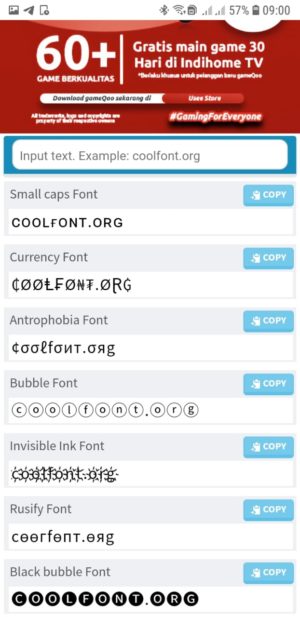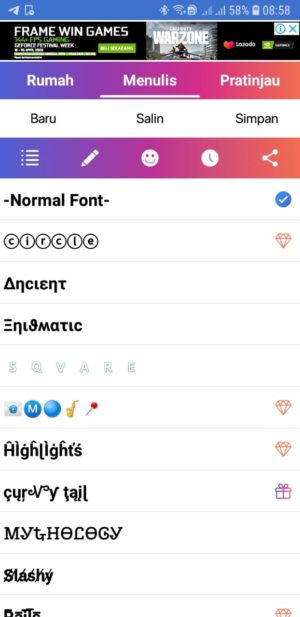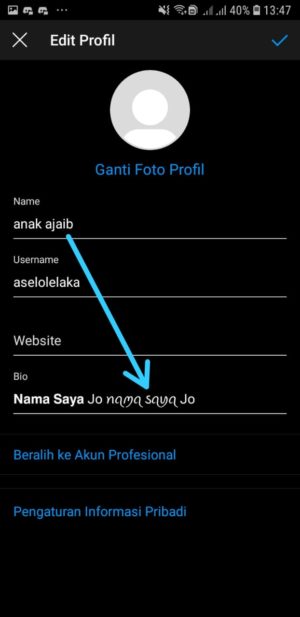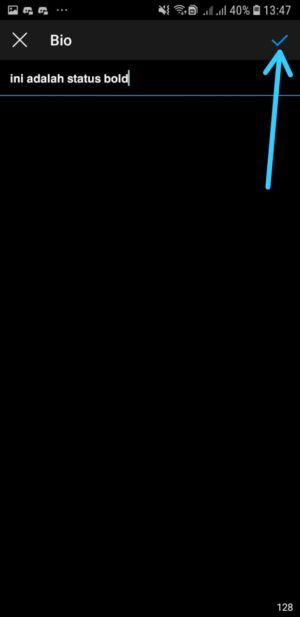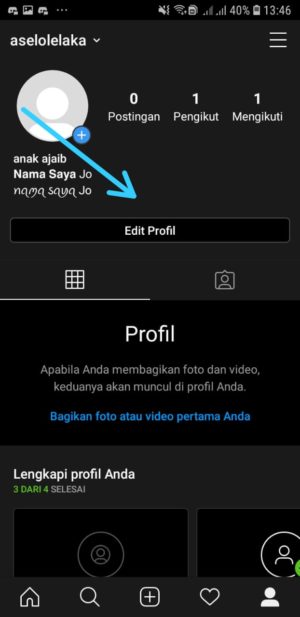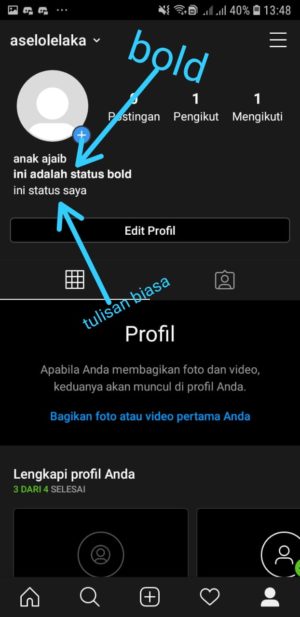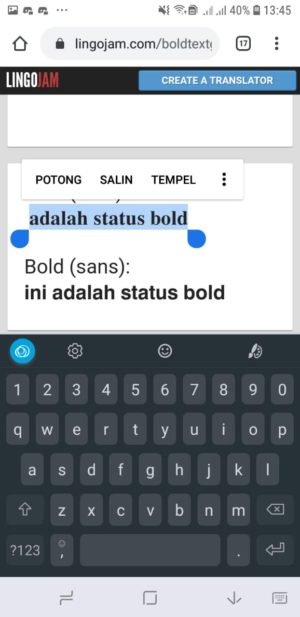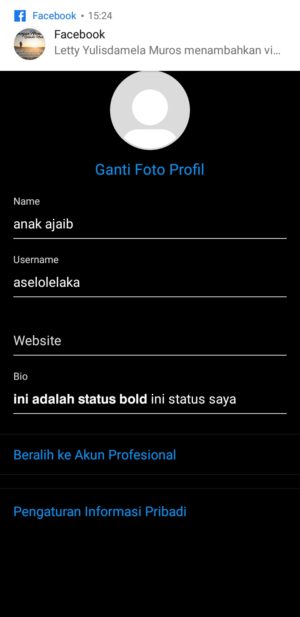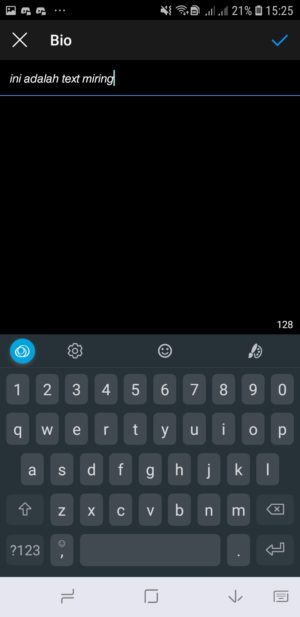
√ Cara Pakai Font Bold, Miring, Atau υɳιƙ Di Bio Instagram
Langsung ke isi Seperti yang kalian ketahui, bio di Instagram merupakan salah satu bagian penting dari profil kita. Tulisan di bio instagram bisa berisi informasi penting atau mungkin berisi quote menarik yang bisa mempercantik tampilan profil kita.
8. Selesai, kalian bisa ubah-ubah kalimatnya sesuai dengan kebutuhan kalian.
Membuat Tulisan dengan Font Unik di Bio Instagram Tidak hanya font tebal dan font miring, kalian juga bisa membuat font dengan model dan gaya gaya yang unik.
Berikut adalah cara mudah memasukkan font unik ke bio Instagram kalian.
Kalian bisa memilih Font yang kalian inginkan seperti huruf bersambung, huruf bergaya klasik, bahkan huruf terbalik sekalipun.
Untuk membuat font unik kalian bisa gunakan cara yang sama dengan membuat font miring. Berikut kita ulangin agar lebih jelas.